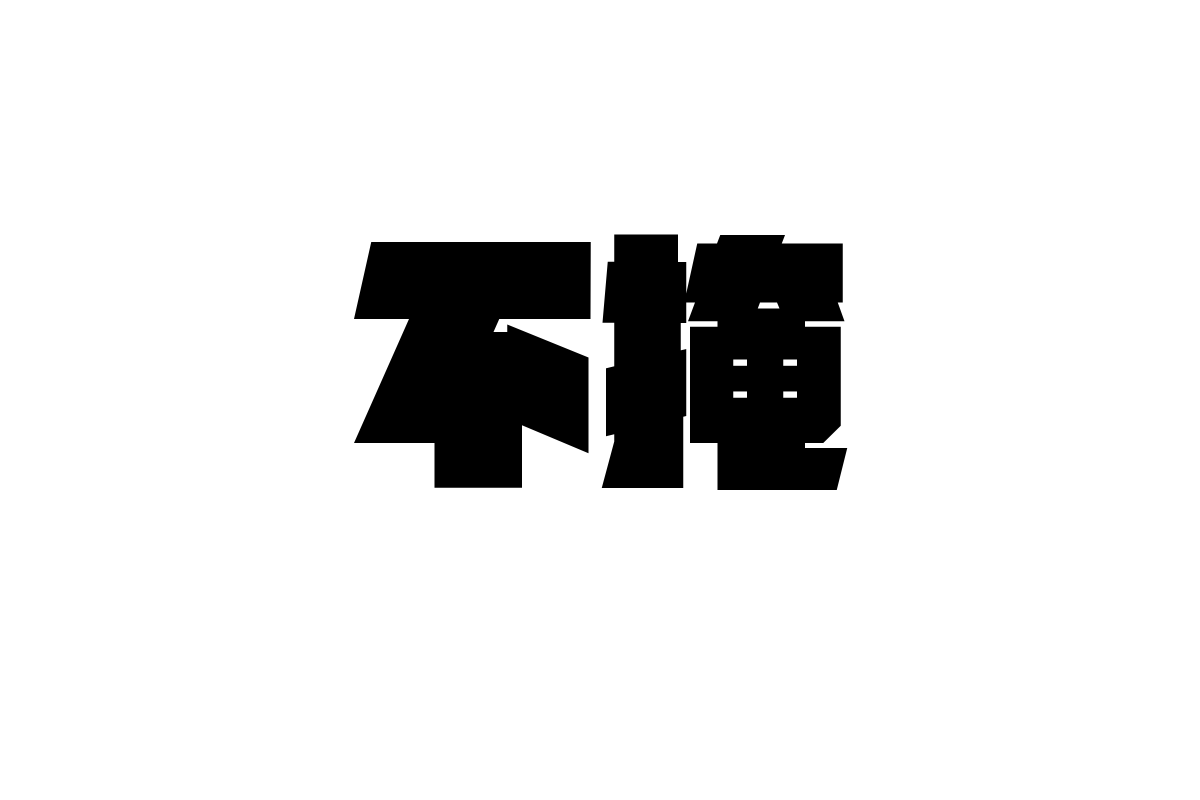
锐字机甲洪荒超级黑字体是一种具有独特设计风格的字体。它采用了现代科技感的设计元素,使得文字看起来更加生动和有趣。这种字体的特点是字形结构紧凑,笔画粗细变化较大,给人一种强烈的视觉冲击。同时,它的线条流畅,给人一种速度感和动感,非常适合用于需要强调速度和力量的场景。
此外,锐字机甲洪荒超级黑字体还具有一定的艺术性。它的字形设计独特,线条流畅,给人一种强烈的视觉冲击力。同时,它的字体大小可以自由调整,可以根据场景的需要选择合适的字体大小。这使得它在各种场合都能发挥出独特的效果。
总的来说,锐字机甲洪荒超级黑字体是一种非常具有个性和创意的字体,适合用于需要强调速度、力量和艺术性的场合。